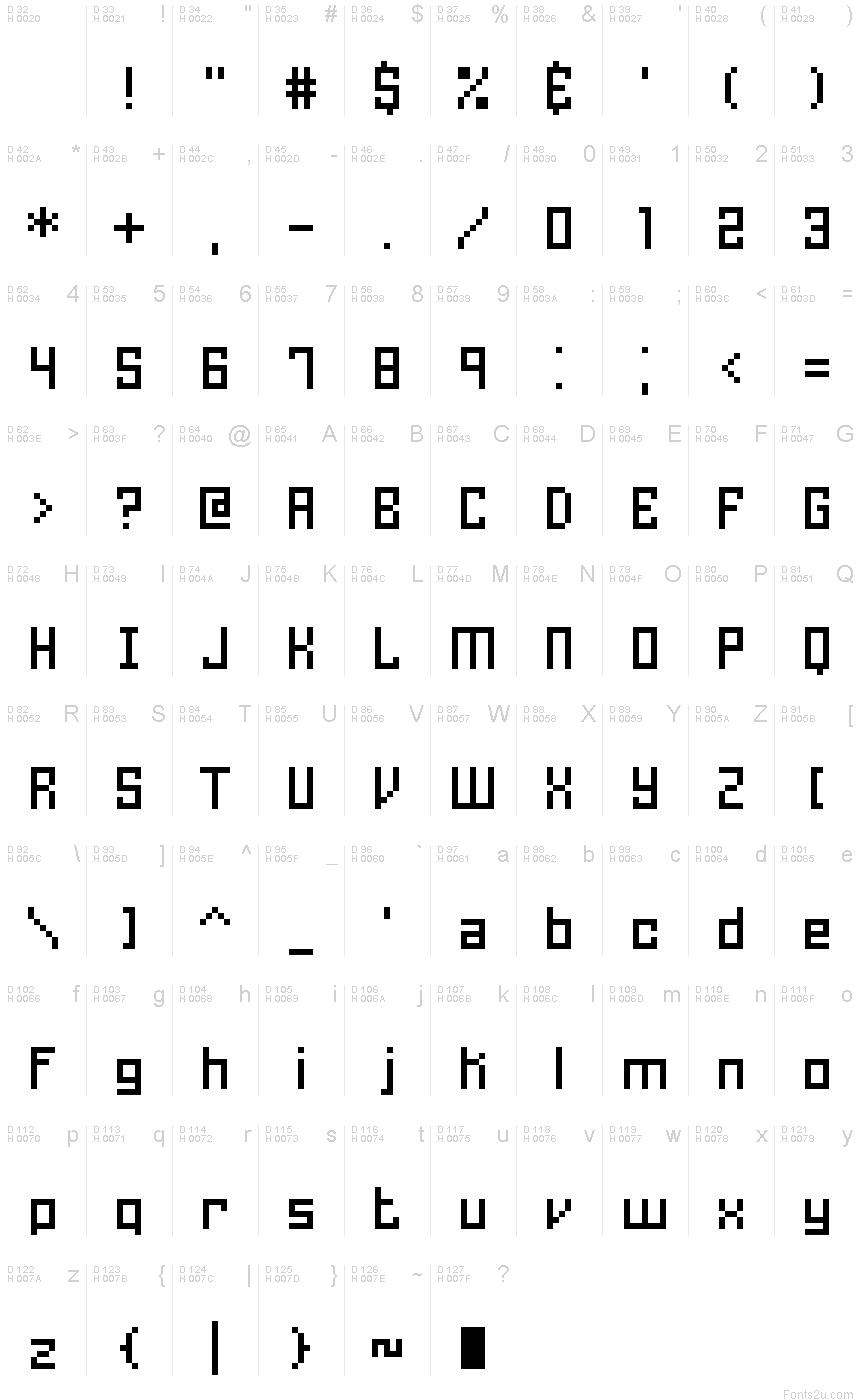
Homespun TT BRK od Ænigma Fonts to darmowy font bitmapowy w stylu pixel art. Jego masywne, modułowe kształty i ostre kąty 90° przywodzą na myśl tekst rodem ze starych monitorów CRT, ale z płynniejszym, bardziej nowoczesnym rytmem, który zachowuje czytelność nawet w małych rozmiarach. Litery łączą się niczym kafelki, nadając projektom zwartą, cyfrową teksturę, która nie sprawia wrażenia przeładowanej.
Dzięki Homespun TT BRK nadasz HUD-om w grach, plakatom pixel art, ulotkom synthwave, retro landing page’om, ekranom powitalnym aplikacji czy brandingowi wydarzeń technologicznych wyrazisty, lo-fi charakter. Ten darmowy font świetnie sprawdza się w odważnych nagłówkach i etykietach nawigacyjnych – najlepiej w połączeniu z prostym fontem bezszeryfowym w dłuższych tekstach. Stosuj go w dużym rozmiarze i z odpowiednimi odstępami, aby pozwolić tym klockowatym formom „odetchnąć” i w pełni wyeksponować ich gridowy charakter.